Шрифти для татуювань фото, ескізи
Татуювання у вигляді написів набувають все більшої популярності. Велику роль відіграє правильний вибір шрифту, адже їх існує дуже багато. Потрібно враховувати стиль написання, місце розташування малюнків, розмір слів. Велика літера повинна бути виділена нахилом, кольором або стилем нанесення.
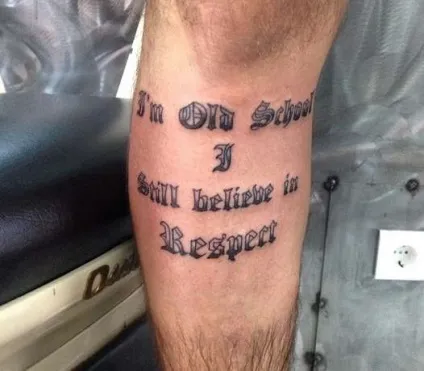
Різні варіації шрифтів дозволять зробити татуювання у вигляді напису красивою і оригінальною
Особливості татуювання шрифти
Татуювання у вигляді написів виглядають дуже оригінально і красиво. Їх дуже люблять наносити на свою справу голлівудські зірки. У деяких випадках напис здатна передати сенс татуювання навіть краще ніж малюнок. Для цього дуже важливо підібрати правильний шрифт. Для жіночих написів підійдуть шрифти з глибокими вигинами, тонкими лініями і додатковим декором. Для чоловічих написів потрібно звернути увагу на друковані літери, застосування жирного накреслення, загострені закінчення. Татуювання шрифти, значення яких більше залежить від сенсу самої написи, однаково поширені, як серед жінок, так і серед чоловіків.
Вибираємо мову і дизайн великої літери
Як правило, шрифт залежить від мови. Однак найбільшою популярністю користується англійська мова. оскільки він вважається світовим. Для татуювання написи, як правило, вибирають шрифти з вензелями і каліграфічні шрифти. Перед нанесенням на своє тіло написи потрібно визначитися: чи буде це слово або ціла фраза. Якщо ви хочете зробити напис, яка починається з великої літери, то потрібно обговорити з дизайнером її особливості, оскільки не кожна велика літера буде добре виглядати. Можливо, дизайнер запропонує вам виділити її окремим кольором або прикрасити додатковими елементами. Татуювання шрифти, фото яких ви знайдете не тільки на просторах інтернету, а й в тату-салонах, дозволять вам підкреслити свою індивідуальність.
Шрифт для татуювання у вигляді напису може бути дуже різним. Якщо ви сумніваєтеся в обраному стилі, краще порадьтеся з дизайнером.
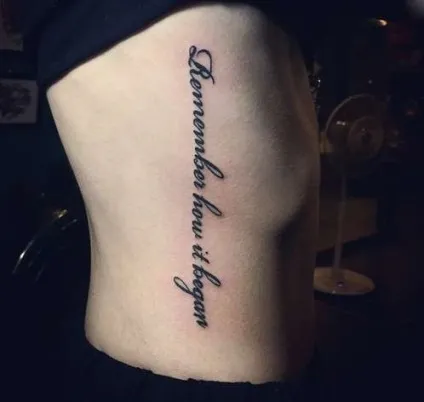
Правильно підібраний шрифт - це основа красивої татуювання у вигляді напису
Будь-яка напис на тілі повинна бути Новомосковскемой, інакше вона не зможе передати той зміст, який ви хотіли в неї вкласти. Відмовтеся від застосування занадто дрібних шрифтів, а також тонких ліній, близько розташованих один до одного. Будь-яке тату з плином часу злегка розпливається, тому ваша напис може перетворитися в одне суцільне пляма.
Види шрифтів для нанесення татуювань у вигляді написів
Татуювання шрифти, ескізи яких є в каталогах салонів для нанесення татуювань, бувають декількох видів. В сучасних тату-салонах віддають перевагу наступним видам шрифтів:
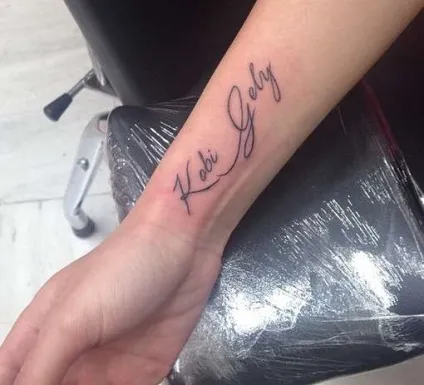
Є й інші види, але саме ці користуються найбільшою популярністю. Варто розглянути їх особливості більш докладно.
каліграфічні шрифти
Цей шрифт вибирають з багатьох причин. Він найбільш розбірливий і зрозумілий, ви без зусиль зможете вибрати літери та знаки, які найбільше підходять за стилем для вашої татуювання. Каліграфічний шрифт може бути класичним, який зробить вашу татуювання схожою на старовинну напис, а також простим, в якому використовуються звичайні літери, написані від руки.
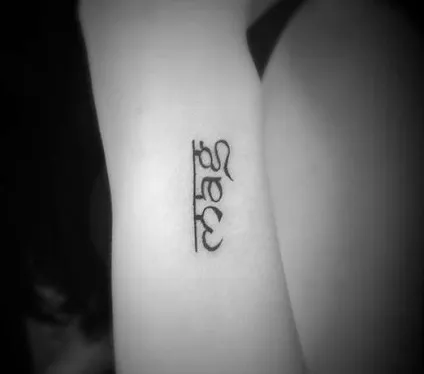
готичний шрифт
Цей шрифт почали використовувати музичні колективи для написання своїх логотипів. Готичний шрифт може бути як складним, так і простим. Від цього буде залежати легкість читання готової написи. Можна використовувати окремі ініціали або цілі написи.
стиль Графіті
Цей стиль є змішення ілюстрації та топографічного шрифту. Він прийшов буквально з вулиць. Ідеї для натхнення ви можете черпати навіть з тих написів, який ви зможете побачити на парканах і у дворах. Однак потрібно пам'ятати про те, що не кожен дизайнер зможете намалювати татуювання в такому стилі.
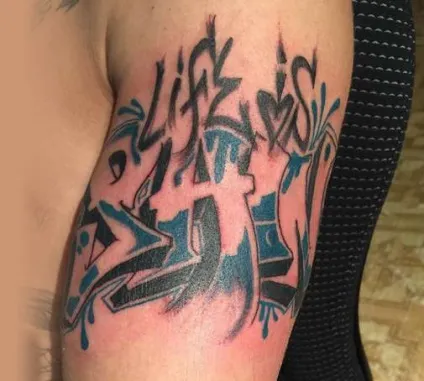
Навіть дуже маленька татуювання може додати вашому образу особливу пікантність
Зовсім недавно у мене виникла ідея нанести на своє тіло татуювання зі словом «Вічність». Я просто відкрив «Фотошоп» і підібрав потрібний шрифт. Дизайнер схвалив результат моєї роботи.
західний шрифт
Напис, виконаний за допомогою такого шрифту, перенесе вас у часи Дикого Старого Заходу. Цей шрифт для нанесення татуювань дуже часто використовують Байкери.
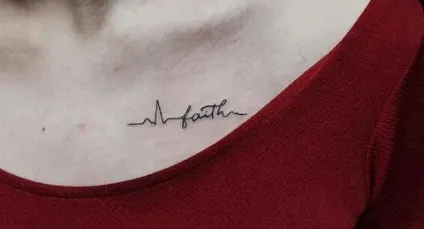
Азіатські, арабські, українські шрифти
Деякі любителі тату вибирають написи, які нагадують про ту чи іншої цивілізації або країні. Зовсім не обов'язково використовувати літери, які використовуються в тій чи іншій країні. Можна просто стилізувати напис. Виглядати таке татуювання буде також дуже красиво.
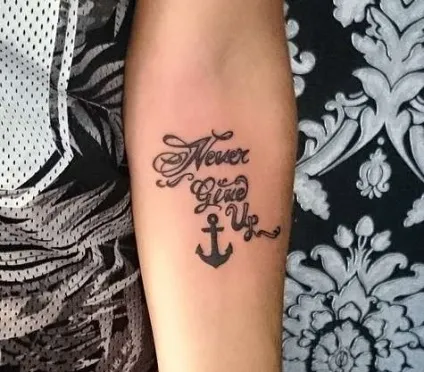
Як вибрати шрифт для татуювання
Написи дуже часто наносяться на область попереку. зап'ястя. щиколотки, задню частину шиї. Саме тут вони виглядають найбільш гармонійно.